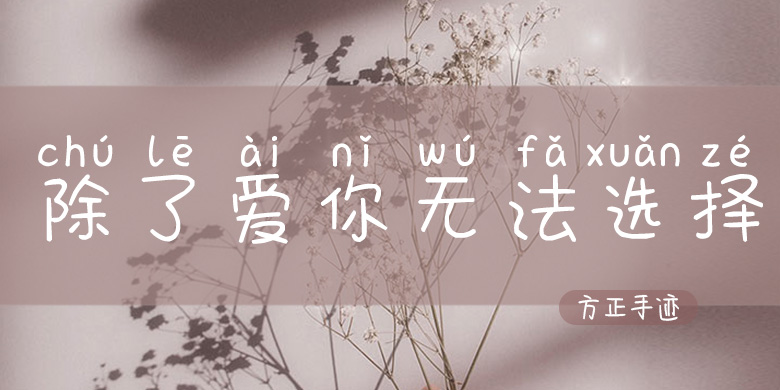
方正手迹-除了爱你无法选择
方正手迹-除了爱你无法选择,这款字体结构工整、笔画清晰,兼顾美观与易读性,适用于标题、正文、海报、包装、LOGO 等多种场景。字形优雅稳定,风格百搭耐看,适配日常排版与创意设计,让文字呈现更舒适、更具质感。方正手迹-除了爱你无法选择一笔一画,皆是细节,以均衡的比例、流畅的线条打造舒适视觉体验,字形端正大气,风格简约现代。无论是商业设计、品牌宣传还是日常排版,都能轻松驾驭,让文字更有格调与力量。方正手迹-除了爱你无法选择字体下载。
字体品牌: 方正手迹 设计师:余丹,俞亦婷 字体分类:创意书写 字体属性:精品字 字符集:大陆简体(GB2312-80) 发布时间: 2020
该拼音体汉字部分在转折处大都采用圆角处理,重心偏中,字面足够大,因而作为拼音体也能保持良好的辨识度。适用于现代诗歌、短文的排版,以及屏显、影视综艺,及文化、商业类品牌的广告语设计。